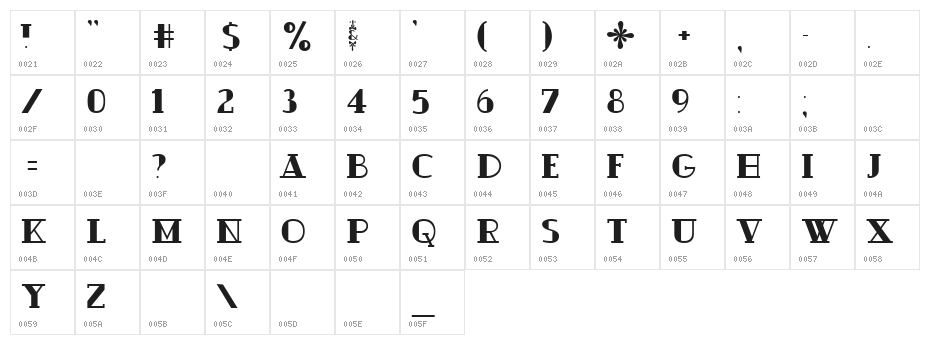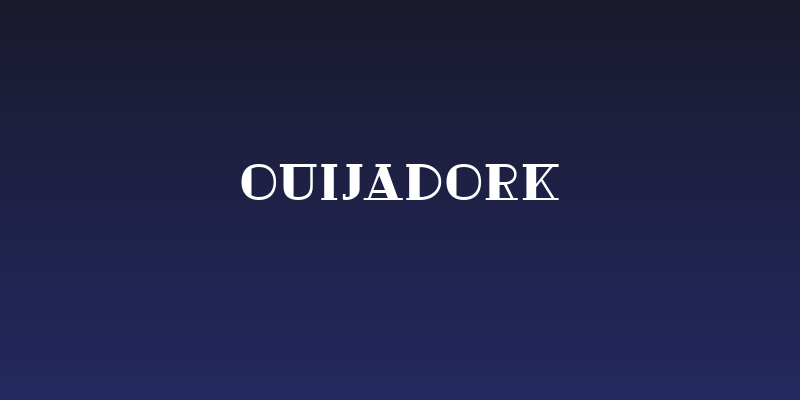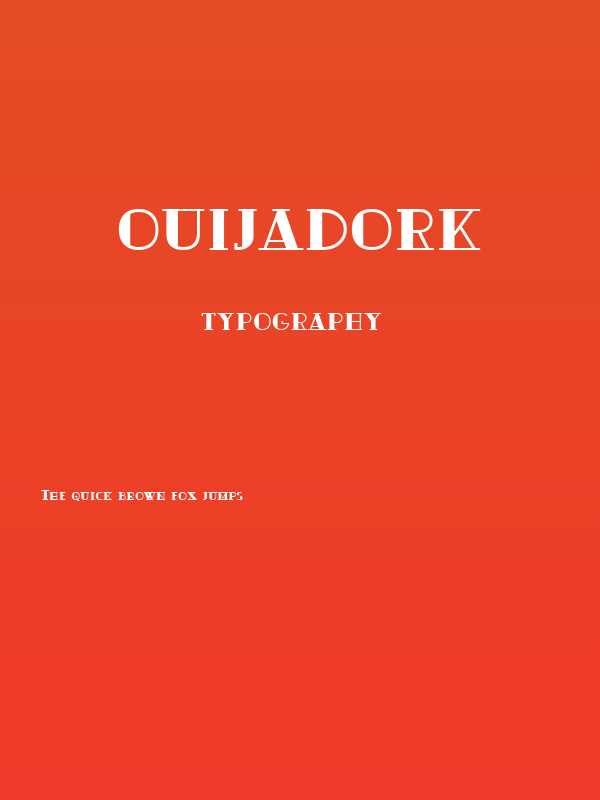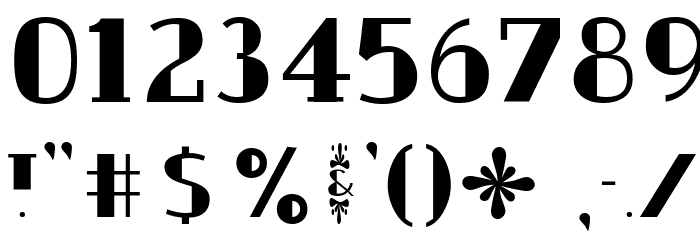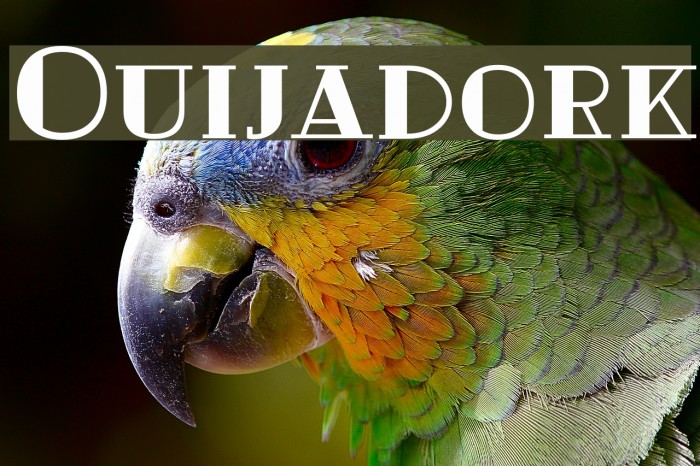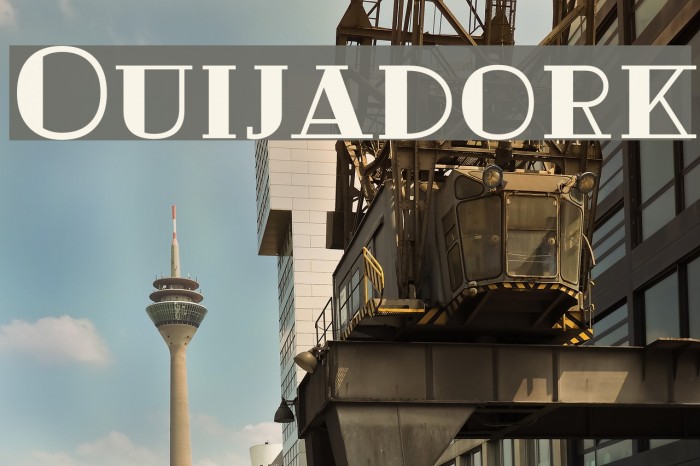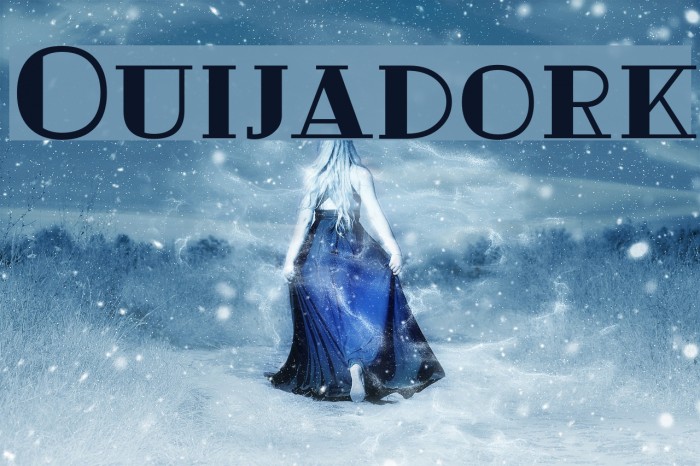
Ouijadork Font
| Gesamtstil | Vintage |
| Vorgeschlagene Projekte | Ideal for posters, branding, headlines, and any design requiring a bold, vintage aesthetic. |